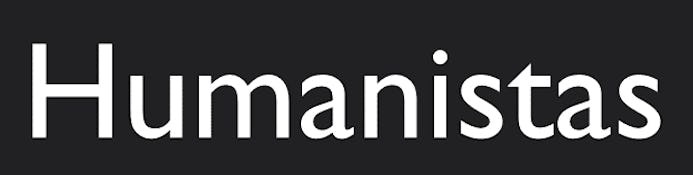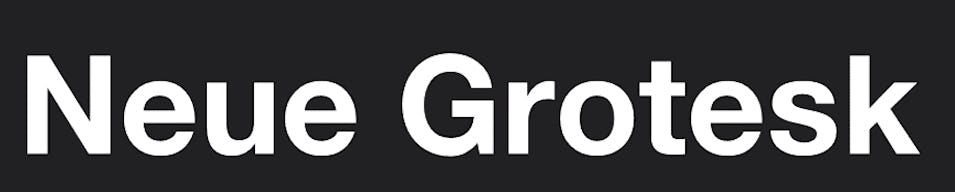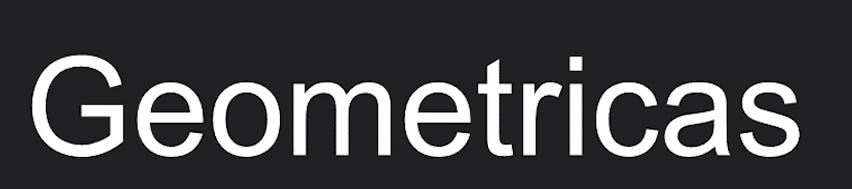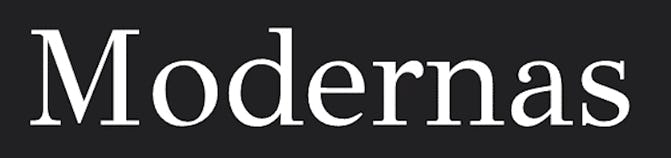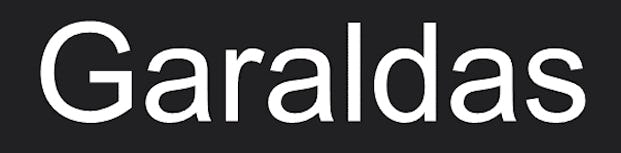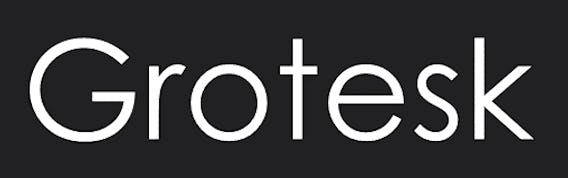
Aunque no lo hayas advertido, los tipos de tipografías y sus características forman parte de tu vida cotidiana.
Todos los días escribes correos electrónicos, lees publicidad por doquier y chateas hasta el cansancio.
Pero, ¿alguna vez te has puesto a pensar qué hay detrás de todas esas letras que ves a diario? Los tipos de fuentes tipográficas te ayudarán a entenderlo.
Por si te preguntas qué es la tipografía y su clasificación, te contamos que es un conjunto de caracteres alfanuméricos que tienen un estilo y varias características en común. Cada tipografía es diseñada siguiendo una serie de parámetros propios del estilo.
En este artículo, conocerás cuáles son los 4 tipos de tipografías y su significado, así como los ejemplos de todos los tipos de tipografías y su aplicación de acuerdo a lo que quieras comunicar.
1. Tipografía Serif
La tipografía Serif se caracteriza por tener letras modernas, pero basadas en las más antiguas. Estas se han utilizado desde los inicios de la impresión y suelen ser usadas por la prensa escrita, así como en la literatura, ya que sus formas ayudan a no perder el hilo del texto.
A este tipo de tipografía se le denomina Serif por las serifas en sus letras, que son los pequeños adornos ubicados en los extremos de cada letra. Ahora, la tipografía Serif se divide en tres estilos de tipografía:
- Humanistas: Tienen una modulación inclinada de trazo quebrado y remates desproporcionados.
- Garaldas: Tienen modulación inclinada de trazo redondeado y también remates desproporcionados, pero se pueden controlar más los trazos.
- Modernas: Muestran distanciamiento completo de las formas de escritura. Su modulación es axial (ángulo recto) y es de acentuado contraste entre trazos finos y gruesos. Sus remates también son desproporcionados.
Ejemplos de tipografía Serif
Chicago Makers
Dentro de los tipos de tipografías en diseño gráfico, existen ejemplos precisos para logos. Este es uno de ellos. Chicago Makers tiene un estilo moderno y puede ser usado en diferentes pesos en espacios que representen el símbolo de la marca. También, es bastante atractivo en banners de publicidad y anuncio de redes sociales.
Mirador
Esta fuente de tipografía muestra una forma neoclásica que se conecta muy bien con el estilo tradicional de la familia tipográfica Serif. Dependiendo de los objetivos de la marca, podría usarse para proyectos arquitectónicos, de espacios urbanos, de diseño de interiores o incluso de moda.
Zin Display
Zin Display tiene una particularidad que la hace un tipo de tipografía de letra llamativa, aunque sin perder su legibilidad: sus terminales puntiagudas. Está hecha para captar la atención y reflejar energía en el diseño. Pueden usarse para proyectos relacionados con el deporte, la música, las conferencias en vivo, etc.
Hacky
A pesar de que en la comparación de formas de tipografías, los ejemplos de fuentes Serif son de los más elegantes y clásicos, Hacky es una fuente que le agrega un toque moderno a ese estilo conservador.
Sus formas ofrecen oportunidades para promocionar productos de lujo, como accesorio de moda, y también para representar temas contemporáneos y más frescos, como la ropa juvenil.
Bodoni*
Hay un ejemplo de fuente tipográfica llamado Bodoni (sin el asterisco). Este caso es una reformulación de ese original. Sus formas circulares y elegantes permiten trazos de letras bastante legibles, por lo que son perfectos para textos de larga extensión, tanto en formatos digitales como en los impresos.
Northden
Esta clase de tipografía está basada en diseño industrial, con foco en la legibilidad y hecho para resaltar en cualquier concepto tipográfico. Tiene un toque bastante retro y nostálgico sin perder su esencia moderna. Sirve para titulares o cuerpos del texto, y por su visibilidad y trazos puede ser aprobado por cualquier proyecto.
Clab
Esta puede convertirse en una de las tipografías más usadas en titulares, headings y espacios que contengan el mensaje principal de un texto. Su característica tipográfica principal es que consiste en un tipo de negrita denso, que puede servir, por ejemplo, en posters, afiches de papel puestos en paredes e incluso en logos que quieran transmitir fuerza.
Style Clubs
Si te estás preguntando qué tipo de tipografía es, esta clase de Serif resalta por sus formas estilizadas que reproducen el entorno de la industria de la moda y los productos fashion. Por supuesto, encajan muy bien en promociones de productos de lujo, como relojes o de cualquier tipo de vestimenta. Asimismo, sirven para tipografías en logotipos de marcas.
Madeline
Al usar este tipo de letra, tienes que pensar en marcas, productos o proyectos creativos. Tiene un estilo tipográfico único, porque refleja trazos hechos a mano, lo cual brinda idea de movimiento y flexibilidad al diseño. Sin duda, es un gran ejemplo de tipografía hecha para los viajes, los eventos sociales o de entretenimiento.
Ahora que ya sabes cuáles son los tipos de tipografía y cuántos tipos de tipografía existen, ¡haz una prueba y verás su utilidad!